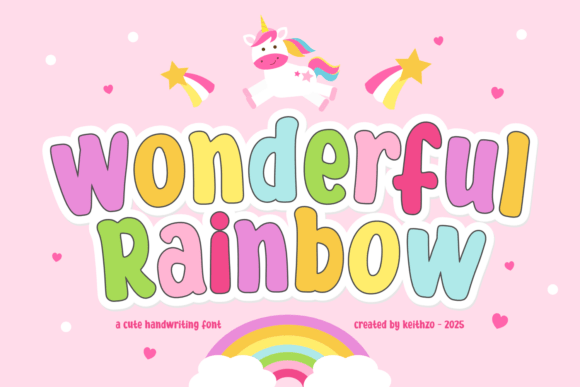
Wonderful Rainbow
適切なデザイン要素を見つけるのは難しい場合がありますが、Wonderful Rainbowは作品を即座に引き立てる優れたコレクションを提供します。
POD(オンデマンド印刷)製品、結婚式の招待状、またはソーシャルメディアのグラフィックを作成している場合でも、Wonderful Rainbowは理想的です。